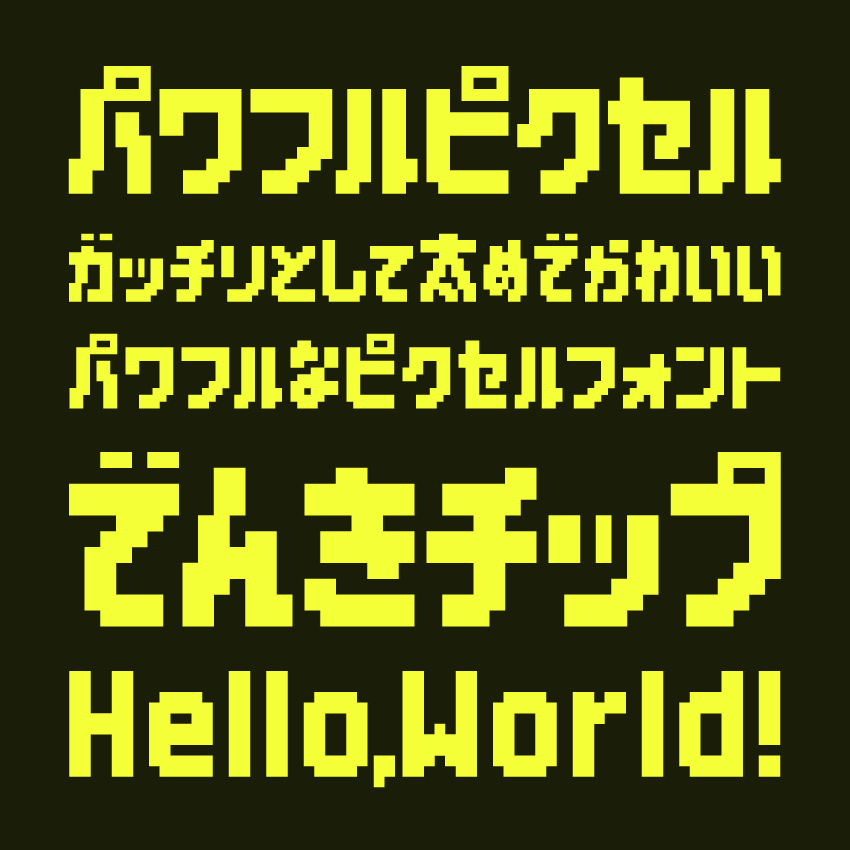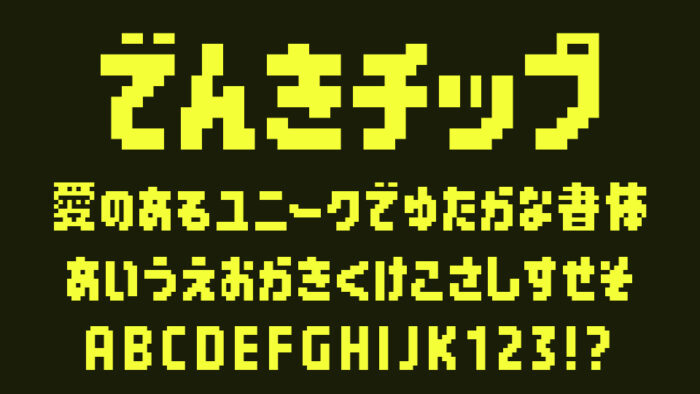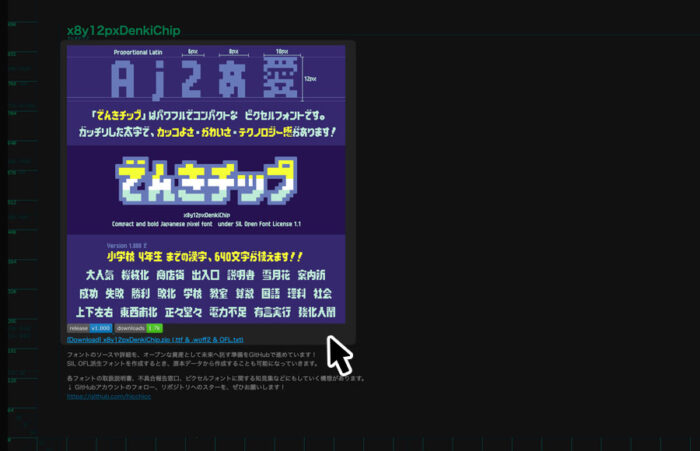
でんきチップ
でんきチップフォントは、ドシッとした太さでかっこよくもありかわいいもあるパワフルなピクセルフォントです。
縦長でコンパクトに作られているのでも、画面上でくっきりとしているので、パワフルで存在感を放ちます。どこか懐かしい8bitの空気をまといながらも、現代のデザインに取り入れやすい整理されたバランス感があるフォントです。
ピクセルフォントなので、ゲームのグラフィックとの相性が良いですが、テクノロジー・サイバー・Y2K・Y3Kといったジャンルなどにもぴったりなフォントです。
収録文字は、漢字(4学年までの漢字)・ひらがな・カタカナ・アルファベット・数字・記号が収録されています。
漢字は今後のアップデートで増えていくとのことです。